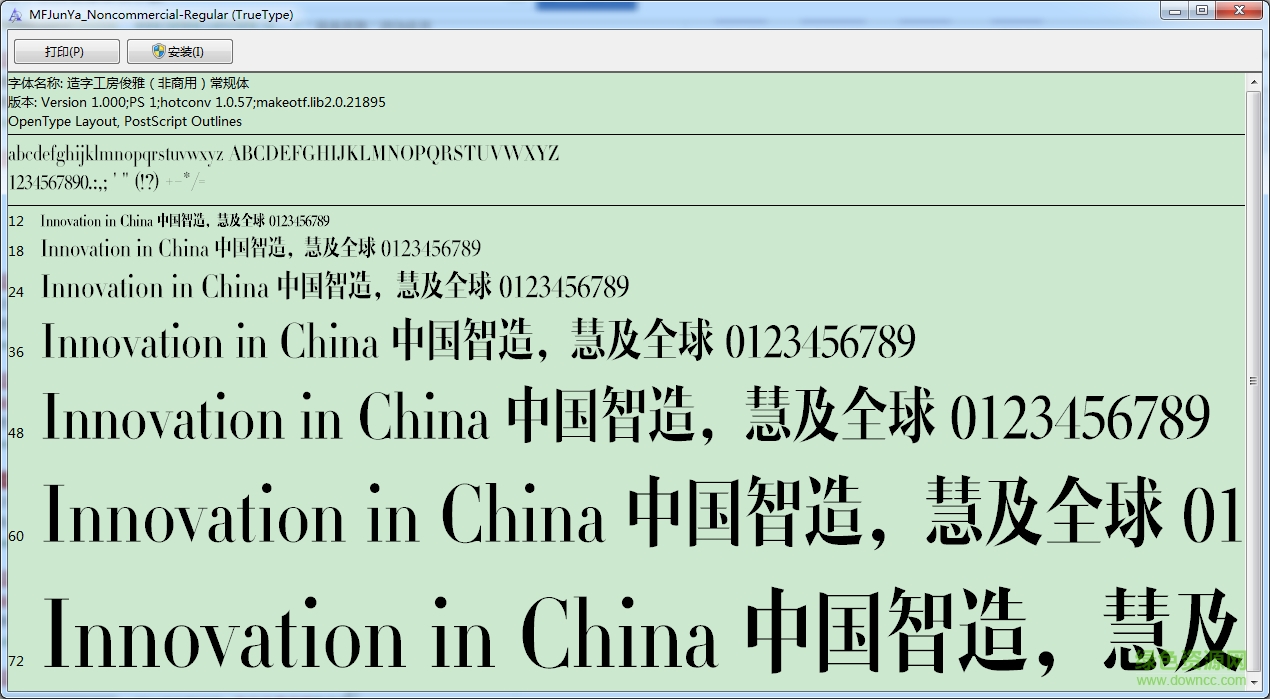
mfjunya noncmmercial regular字體又稱造字工房俊雅(非商用)常規(guī)體,該字體支持中英文輸入,筆畫簡約,秀美得體,給人感覺生動(dòng)可親,適合用于排版設(shè)計(jì),歡迎大家前來下載!
1.整套字體的設(shè)計(jì)精益求精,相比傳統(tǒng)宋體,多達(dá)近十項(xiàng)創(chuàng)新;
2.造字工房俊雅體一改傳統(tǒng)宋體的間架結(jié)構(gòu),對其進(jìn)行了大膽的創(chuàng)新設(shè)計(jì),使其筆畫更加簡潔、時(shí)尚;
3.此款字體適用于時(shí)尚行業(yè),主作標(biāo)題與副標(biāo)題之用。